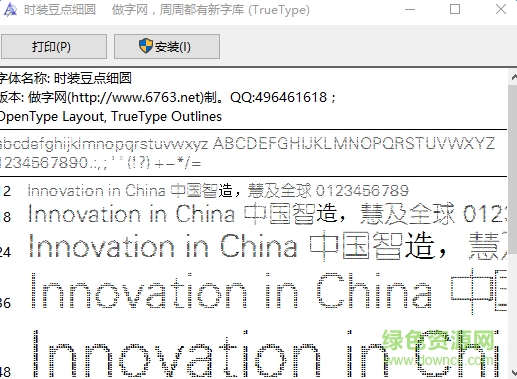
時(shí)裝豆點(diǎn)細(xì)圓體
時(shí)裝豆點(diǎn)細(xì)圓體是一款很有個(gè)性的電腦藝術(shù)字體,這款字體不像普通的字體那樣呆板,它有著自己獨(dú)特的魅力,也正是因?yàn)槿绱瞬艜?huì)深受廣大朋友們的喜歡,歡迎有需要的朋友來綠色資源網(wǎng)下載。
時(shí)裝豆點(diǎn)細(xì)圓體是一款很不錯(cuò)的電腦字體,寫出來的字是非常的美觀,而且效果很不錯(cuò)的,喜歡這款字體的朋友可以來綠色資源網(wǎng)下載。